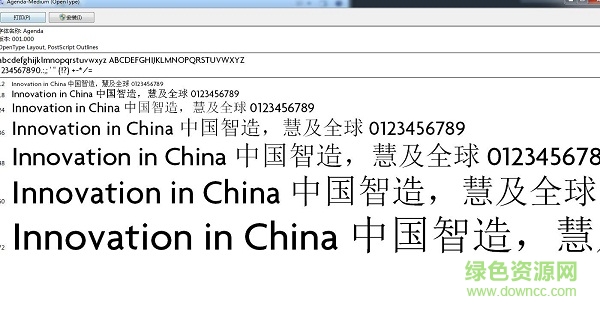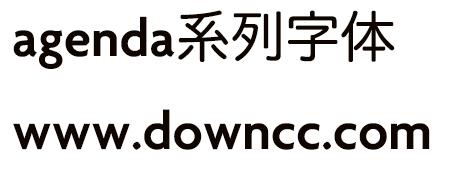
軟件介紹 軟件標簽: agenda字體 無襯線字體 agenda系列字體包收錄了agenda bold字體、agenda light字體、agenda semibold字體、agenda medium字體等多款高品質的無襯線字體,外形美觀,富有韻律,有需要者歡迎前來免費下載!字庫分類【按編碼】:GB2312、GBK、GB18030等等;【按語言】:簡體字庫、繁體字庫、GBK字庫等等;【按風格】:宋體、仿宋體、楷體、黑體、隸書、哥特體(Gothic)等等。優(yōu)秀字體推薦agencyfb-reg 字體 常規(guī)體授權:免費軟件 WinAll, WinXP, Win7大?。?5KB語言:中文agencyfbreg是什么字體?agencyfbreg字體是一款免費的常規(guī)英文字體,四四方方,工整對稱,特征突出,易于辨識,agencyfb系列字體本站都有提供,歡迎免費下載!字體性格分類任何字體都有其獨特的風格,有的讓人感覺現(xiàn)下載地址montserrat-regular 授權:免費軟件 WinAll, WinXP, Win7大?。?8KB語言:中文montserratregular字體是一款經典的無襯線字體,字形工整,結構飽滿,毫無粗細變化,適合用于排版或廣告用字,歡迎大家在綠色資源網(wǎng)下載!字體創(chuàng)意的來源無論漢字,還是拉丁字,任何字體的形成、變化都體現(xiàn)于基本筆形下載地址agenda字體安裝方法1、點擊打開字體,直接選擇安裝即可。2、將字體復制到C:\Windows\Fonts文件夾即可完成安裝。 軟件截圖 上一張下一張(1 / 1) 安裝詳細截圖 其他版本下載 標題 大小 更新日期 下載 下載地址 電腦版 agenda bold字體 點擊報錯 軟件無法下載或下載后無法使用,請點擊報錯,謝謝! 關閉報錯反饋 請描述您所遇到的錯誤,我們將盡快予以修正,謝謝! *必填項,請輸入內容 本類最新 sounso beauty字體 spyced哥特英文字體 ttf版 zerodegrees字體 the next font ttf版 coolvetica font keep calm ttf 免費版 相關文章 俠客風云傳攻略 我叫mt4哪個職業(yè)輸出最高 我叫mt4輸出最高的職業(yè)排行 用Windows 2003系統(tǒng)架設郵件服務器 在Windows 2003中配置ASP.Net環(huán)境 oracle Export and Import 簡介 Linux(CentOS)服務器/VPS上安裝DirectAdmin 用戶評論 熱門評論 最新評論 發(fā)表評論 查看所有評論(0) 昵稱: 請不要評論無意義或臟話,我們所有評論會有人工審核. 字數(shù): 0/500 (您的評論需要經過審核才能顯示)